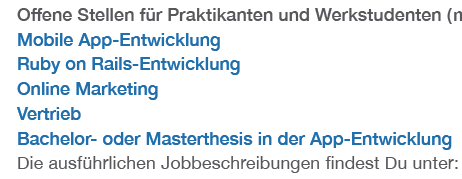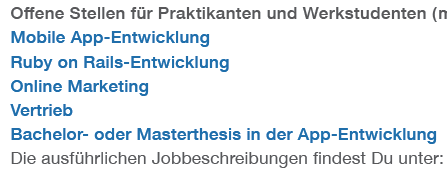
Helvetica Neue "springt" im PDF
ich bin ganz neu hier und bin mir nicht sicher, ob ich mein Problem jetzt am richtigen Ort untergebracht habe. Bitte einfach verschieben, wenn das nicht der Fall sein sollte.
Kurz zu mir, bevor ich zur Problematik komme: Ich bin kein ausgebildeter Designer, sondern komme allgemein aus der Kommunikationsecke. Da ich aber ein sehr design- und gestaltungsaffiner Mensch bin und sowohl im Studium als auch nebenbei an vielen Designprojekte gearbeitet habe, arbeite ich nun auch in meinem Job viel mit Gestaltung. Es kann deshalb aber sein, dass mir grundlegende (bspw. handwerkliche) Aspekte, die für euch ganz natürlich sind, nicht naheliegend erscheinen. Dies bitte ich dann zu entschuldigen. :)
Zu meiner Problematik – die ich euch grob strukturiert habe:
Ausgangssituation:
Ich arbeite in InDesign CC (2014) an einem Dokument, das als PDF online verbreitet werden soll.
Für das Dokument habe ich die Helvetica Neue verwendet, da das die Hausschrift ist – folgende Schnitte habe ich dann gewählt:
Headline: Medium in 14 pt
Subhead: Medium in 11 pt
Copy: Regular in 11 pt
Dann habe ich das Ganze exportiert als PDF (sowohl Print, als auch Interactive).
Problematik:
Geöffnet mit dem Acrobat Reader Pro "springt" die Typo im PDF. Hierbei ist kein Schema erkennbar. Also "wenn die Schrift zu klein ist, wird sie falsch dargestellt" oder ähnliches. Im Gesamtbild (bei einer Darstellung von ca. 60 %) wirkt die Schrift sehr unruhig – sowohl in den Headlines als auch in der Copy. Manche Buchstaben vollführen einen richtigen Tanz.
Und dann wird es noch unverständlicher für mich:
Bei 97 % sieht die Schrift richtig kaputt aus, die Minuskeln scheinen irgendwie abgeschnitten.
Bei 103 % Darstellung sieht die Schrift völlig okay aus.
Und bei 105 % sieht sie dann wieder vollkommen kaputt aus – genau wie bei 97 %.
In Preview geöffnet gibt es keinerlei Probleme, die Typo sieht vollkommen gut aus.
Meine bisherigen Lösungsansätze und deren Tücken:
01: Natürlich könnte ich die Schrift in Pfade umwandeln, aber dann wäre der Text nicht mehr kopierbar und das möchte ich nicht.
02: Ein JPEG rauslassen und das dann umwandeln. Selbe Problematik wie oben, zudem wird die Auflösung bei starkem Reinzoomen natürlich schlechter.
03: Andere Typo wählen: Habe Arial und Helvetica, dort gibt es keine so großen Probleme. Die Arial funktioniert vollkommen, die Helvetica sieht im Gesamtbild auch nicht ganz klar aus, springt aber zumindest nicht so schlimm bei den angesprochenen Zoompunkten (97 % – 103 % – 105 %). Über eine andere Typo könnte ich es also lösen, aber da Helvetica Neue als Hausschrift eingesetzt werden soll, will ich mich mit dieser Lösung noch nicht zufrieden geben.
Meine Fragen:
01: Hat jemand eine Idee, was ich noch versuchen könnte, bzw. woran es liegen könnte?
02: Eignet sich Helvetica Neue einfach grundsätzlich nicht für einen Longcopy-Einsatz? Bzw, gibt es einfach Tücken bei der Typo? Und funktioniert es in der Preview nur, weil es eine Systemschrift auf dem Mac ist?
03: Wenn das ein grundsätzliches Helvetica Neue-Problem sein sollte, hat dann jemand Typo-Vorschläge, wie ich bspw. die Helvetica Neue für den Claim und hervorgehobene Statements etc. einsetzen kann und sie dann mit einer passenden Fließtextschrift ergänzen kann?
Erst mal so weit. Sorry, dass gleich mein erster Beitrag so lang geworden ist. Ich hoffe, ich das Problem klar genug geschildert und einer von euch kann mir gegebenenfalls weiterhelfen.
Schon mal vielen Dank und liebe Grüße
Hallo Ralf,
schon mal vielen Dank für dein Feedback. Ich hab oben noch zwei Screenshots angehängt. Der erste zeigt die beschriebene Problematik bei 105 % Darstellung. Der zweite die Darstellung bei 103 %.
Du meinst die Einstellungen zur Darstellung im Acrobate Reader? Wenn ja, dann kann ich das ausschließen. Sah auch auf anderen Rechnern im Acrobate so aus.
Okay. Also wie gesagt: solche Sprünge entstehen durch das Zusammenspiel von Font-integriertem Hinting und der jeweils benutzten Render-Engine der Software. Der Adobe-Reader hat seine eigene – daher tritt das Problem auch nicht in der Vorschau auf.
Was ist das denn für eine Helvetica-Version? Welches Font-Format? Wie alt? Eventuell mal konvertiert worden?
@Ralf: .dfont, Version 9.0d57e1, aus 2013 – von Konvertierung o.ä. ist mir nichts bekannt. Hilft dir das für eine Einschätzung?
Hatte vorher aber schon das gleiche Problem mit der auf dem Mac vorinstallierten Helvetica.
@catfonts: Danke für den Tipp. Ich hab nach einem Download gegoogelt, finde aber nur Links, die mir dubios erscheinen. Hast du da eine verlässliche Quelle?
Ja, direkt auf der Hersteller-Seite: http://www.foxitsoftware.com/german/downloads/
Hier die englische Version wählen, ist die aktuellste, und erst nach der Installation über File - Preferences - Language die Sprache auf Deutsch ändern (wenn überhaupt nötig) - dann wird eine Sprachdatei nachgeladen.
"Ich hatte da gleich die Assoziation mit der lästigen Adware und war dann gleich wieder weg. :)"
bei meiner Quelle ist es Adware-Frei, wirklich eines der wenigen Programme, und ich habe schon oft erlebt, dass es PDF-Dateien besser anzeigt, als der Adobe-Reader.
hilft ja nicht viel, wenn man ein pdf einer größeren gruppe von empfängern zugänglich machen will. die werden nicht alle den foxit reader runterladen, weil das rendering der mac-true-type-helvetica im adobe reader nicht optimal ist.